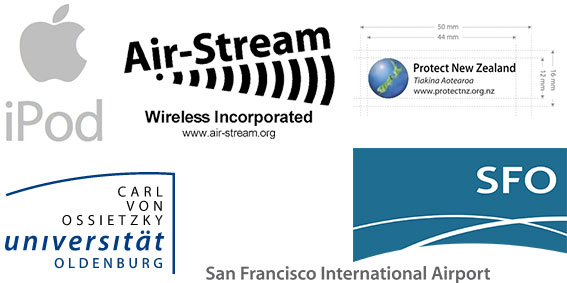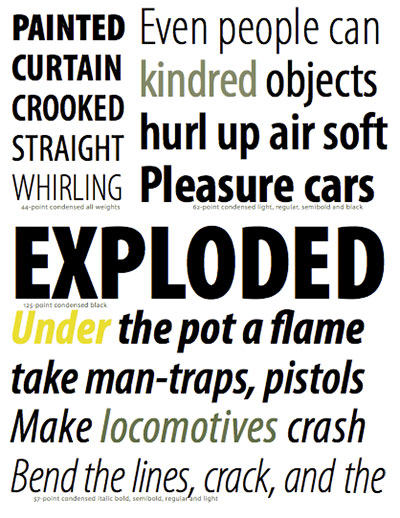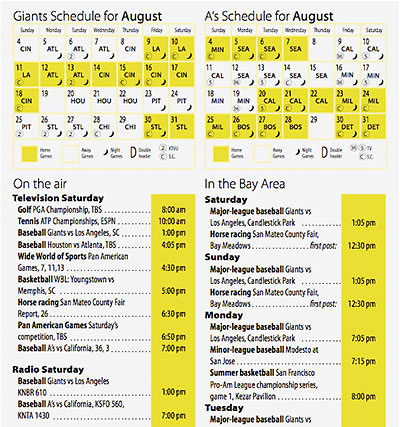
Myriad: perfekt in Form und TechnikDie Adobe-Originalschrift Myriad war in technischer Hinsicht stets
Vorreiter: 1992 als erste Multiple-Master-Schrift, 10 Jahre später als
OpenType-Vorzeigefont. Carol Twombly und Robert Slimbach entwarfen sie
systematisch als Großfamilie für mehrere Sprachräume. Auch
![]() Wie bei jeder Schrift, ist auch das Aussehen der Myriad-Familie
geprägt von den Werkzeugen ihrer Zeit. Im Jahre 1992 führte Adobe die
atemberaubende Multiple-Master-Technik (MM) ein, für deren
Fähigkeiten es keinen historischen Vorläufer in der Schriftgeschichte
gab. Eine Multiple-Master-Schrift wird mit visuellen Achsen angelegt, zum
Beispiel für die Strichstärke (weight = Fette), die Buchstabenbreite
(width) oder die optische Größe. Über das aufgespannte zwei-
oder dreidimensionale Koordinatensystem lassen sich Tausende von
Schriftzuständen (= Schriftschnitte einer Familie) erstellen – ohne
dass die Buchstabenformen durch Stauchungen oder Verzerrungen zerstört
würden.
![]() Zweiachsige (weight, width) Multiple-Master-Schrift Myriad; rot gekennzeichnet: der Grundschnitt Eine erkleckliche Anzahl von Basisschnitten wurden von Hause aus mit jedem Multiple-Master-Font geliefert. Darüber hinaus konnten sich die Anwender beliebig viele Zwischenstufen auf einfach Weise selbst generieren. Im Editorial-Bereich war die Multiple-Master-Technik ein Segen, weil man mit ihr die Mikrotypografie perfekt abstimmen konnte: Überschriften und Text mit genau definierten Stärken, Headlines mit benutzerdefinierter Breite, oder Tabellenschriften, die perfekt in starre Raster passten (zum Beispiel bei Fernsehprogramm-Zeitschriften). Doch die von Adobe entwickelte Technik setzte möglicherweise ein mikrotypografisches Feingefühl voraus, das manche Anwender überforderte. Nur so ist es zu erklären, das Multiple-Master-Fonts heute keine Rolle mehr auf dem Font-Markt spielen. Da Adobe den für die MM-Erzeugung notwendigen Adobe Type Manager (ATM) nicht mehr weiter entwickelt, wird die Technik bald aussterben. Carol Twombly und Robert Slimbach entwarfen die Myriad 1992 von Anfang an als zweiachsige Multiple-Master-Schrift. Es war die erste Sans-Serif-Schrift unter den Adobe Originals. Wie ihre Verwandten Frutiger oder Syntax klassifiziert man sie als humanistische Sansserif, weil sie keinen gleich starken Strich aufweist (wie zum Beispiel Futura), sondern einen Strichstärkenkontast. Das Vorbild hierfür sind die Antiqua-Schriften: Myriad ist nicht geometrisch konstruiert, darüber hinaus überragen die Oberlängen der Gemeinen (l, h, f, ...) die Großbuchstaben – wie bei vielen Serifenschriften. Natürlich weisen auch Myriads Italic-Schnitte die klassischen Eigenschaften auf: geschlossenes a, f mit Unterlänge und von Hand abgestimmte Kursivformen statt Schrägstellung. ![]() Typische Merkmale der humanistischen Sansserif Myriad: Strichstärken-Kontrast, Oberlänge höher als die Versalien, echte Kursive Wenn man sich nicht der Multiple-Master-Version der Myriad bedienen möchte, stehen die Teilfamilien Myriad Condensed (6 Schnitte), Myriad Normal, Myriad Semi Extenden und Myriad Extended zur Auswahl. Sonderformen sind die Trash-Fonts Myriad Tilt und Myriad Sketch. Aufgrund ihrer Vielfalt ist Myriad die perfekte Schrift fürs Corporate Design, wo sie von der Visitenkarte bis zum Großflächenplakat funktioniert. Ungezählte Firmen und Institutionen haben sie sich als Hausschrift verordnet. Als vor zwei Jahren Apple auf Myriad umstieg, bescherte das der Schrift neue Popularität. ![]() Myriad ist eine beliebte Corporate-Schrift; sie spielt die typografische Hauptrolle in der Kommunikation von Apple, Wireless Inc., dem Neuseeländischen Umweltverband, der Universität Oldenburg und dem Flughafen von San Francisco Auch im Verlagswesen und im Editorial-Bereich ist die Familie sehr beliebt: Im Kleinen löst sie alle typografischen Herausforderung, auf den Titelseiten und Schutzumschlägen vermittelt sie Seriosität und Charakter. Als das Berliner Designunternehmen MetaDesign Anfang der 90er Jahre für den wissenschaftlichen Springer-Verlag ein umfangreiches Gestaltungskonzept erarbeitete, spielten die Myriad – zusammen mit ihrer »Schwester« Minion – die erste Geige. MetaDesign nutzte die Multiple-Master-Technik, um die Schriften fein aufeinander abzustimmen. Bis heute arbeitet der Verlag mit diesen individuell erstellten MM-Schnitten. ![]() Eine von MetaDesign Anfang der 90er Jahre erstellte Myriad-Multiple-Master wird noch heute vom Springer Verlag für die Umschlaggestaltung eingesetzt Myriad vs. Frutiger Seit Erscheinen der Myriad gibt es Stimmen, die sie als Kopie der Frutiger bezeichnen (zum Beispiel die des Heidelberger Schriftenfreunds Ulrich Stiehl: »... in the case of ›Myriad‹, Slimbach made a forgery of Adrian Frutiger’s ›Frutiger‹, and Adobe labeled this forgery as ›Myriad‹ and is selling it as ›Original‹.«) Dieser Argumentation kann ich mich nicht anschließen, und ich kenne eigentlich keinen Schriftentwerfer, der Ähnliches denkt (einschließlich Adrian Frutiger). Sicher sehen diese Genies Schriften mit anderen Augen. Sie erkennen Unterschiede, die sich einem Laien beim besten Willen nicht erschließen. Darunter muss man genauso wenig leiden wie unter der Unfähigkeit, beim Hören einer unbekannten Sonate diese als Beethoven- oder Mozart-Komposition zu identifizieren. Natürlich sind beide Schriften gleichen Ursprungs und sie zielen auf vergleichbare Anwendungsgebiete. Doch bei aller Ähnlichkeit legen ihre Entwerfer doch Wert darauf, ihrer eigenen Handschrift gefolgt zu sein. Adrian Frutiger hat mit seiner Schrift die Klasse der humanistischen Sansserif eigentlich erst begründet: auch wenn es zuvor Vergleichbares gab, so hat er dieser Idee zum Durchbruch verholfen. Myriad reiht sich in diese typografische Klasse ein, man sieht ihr aber auch an, dass sie 20 Jahre später entstand. ![]() ![]() Vergleich Frutiger (jeweils oben) und Myriad (darunter): Schriften gleicher Stilistik, aber unterschiedlich interpretiert Myriad Pro Seit Einführung der OpenType-Standards ist die Schrift Myriad in diesem Format lieferbar. Sie war eine der ersten OpenType-Pro-Schriften, womit Adobe (und inzwischen andere Hersteller gleichermaßen) kennzeichnet, dass ihre Fonts OT-Features mitbringen, zum Beispiel typografische Automatiken und Fremdsprachen-Unterstützung. Im OpenType-Format bietet Adobe die Myriad als 4 Teilfamilien an: Myriad Pro (PDF mit allen Figuren und Schnitten), Myriad Pro Condensed (PDF mit allen Figuren und Schnitten), Myriad Pro Semi Condensed (PDF mit allen Figuren und Schnitten) und Myriad Pro Semi Extended (PDF mit allen Figuren und Schnitten). Insgesamt sind dies 40 OpenType-Fonts, die umgerechnet rund 200 bis 300 PostScript-Schriften entsprechen, denn die OpenType-Fonts enthalten nicht nur jede Menge Expert-Zeichen und Ziffern-Sätze, sondern auch alle griechischen und kyrillischen Buchstaben. ![]() Beliebtes Einsatzgebiet für die Myriad-Font-Vielfalt: komplizierte Tabellen, strukturierte Listen und Übersichten Dieser Report kann die Myriad-Geschichte und die Möglichkeiten der ausgereiften Schrift nur streifen. Zur weiteren Lektüre empfiehlt sich dieses PDF zur Myriad Pro (1,3 MB), das auf 93 Seiten die Familie in aller Ausführlichkeit darstellt: inklusive Schriftmuster, Anwendungsbeispiele und Historie. Herausgegeben: Fr - August 26, 2005 at 02:38 nachm. | |